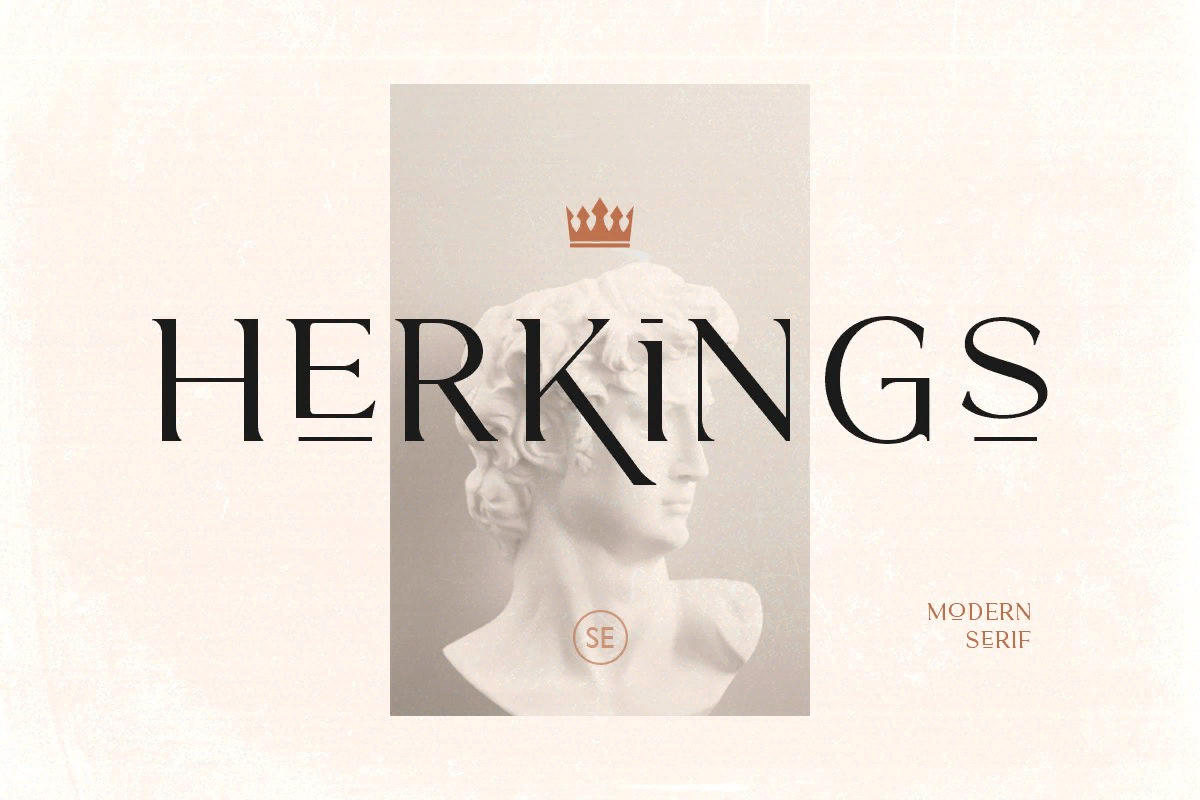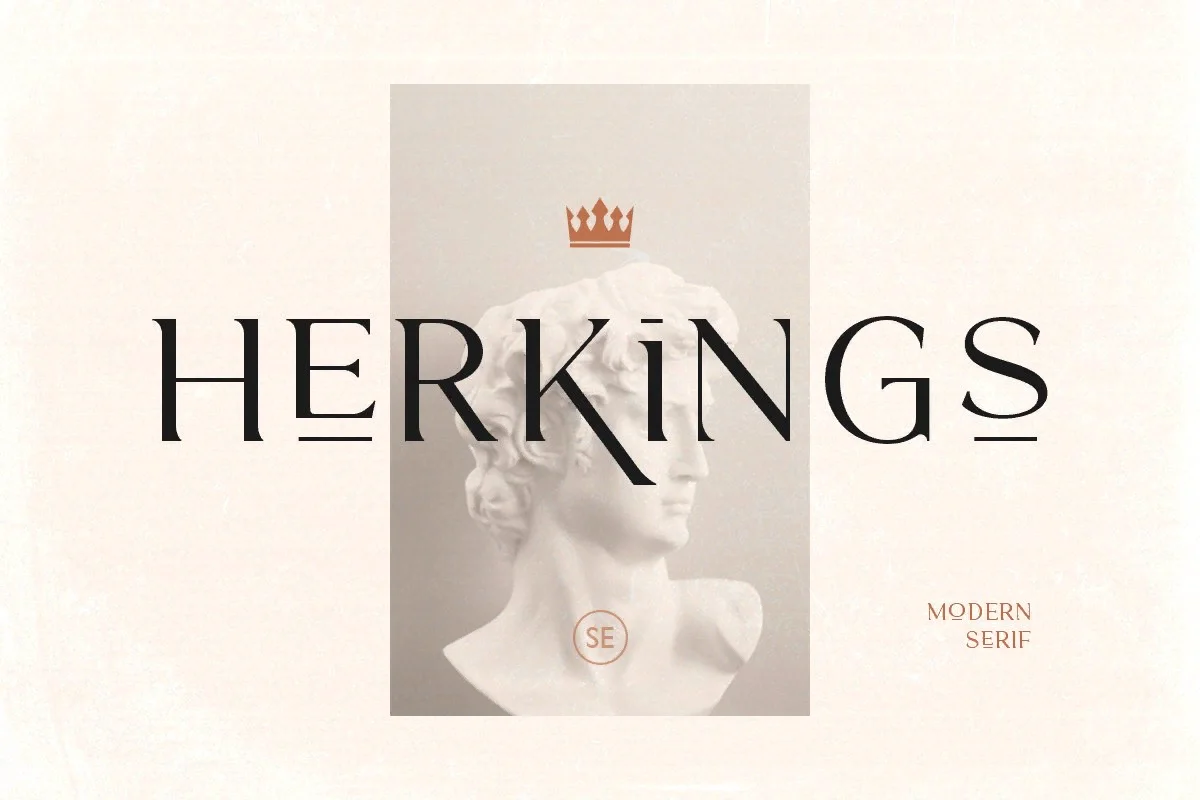
Название: Herkings Font (2021)
Herkings - это минималистичный и современный шрифт с наклонной засечкой, универсальный и уникальный.
Его можно использовать для брендинга, логотипов, визитных карточек, дизайна одежды, фильмов, журналов и многого другого!